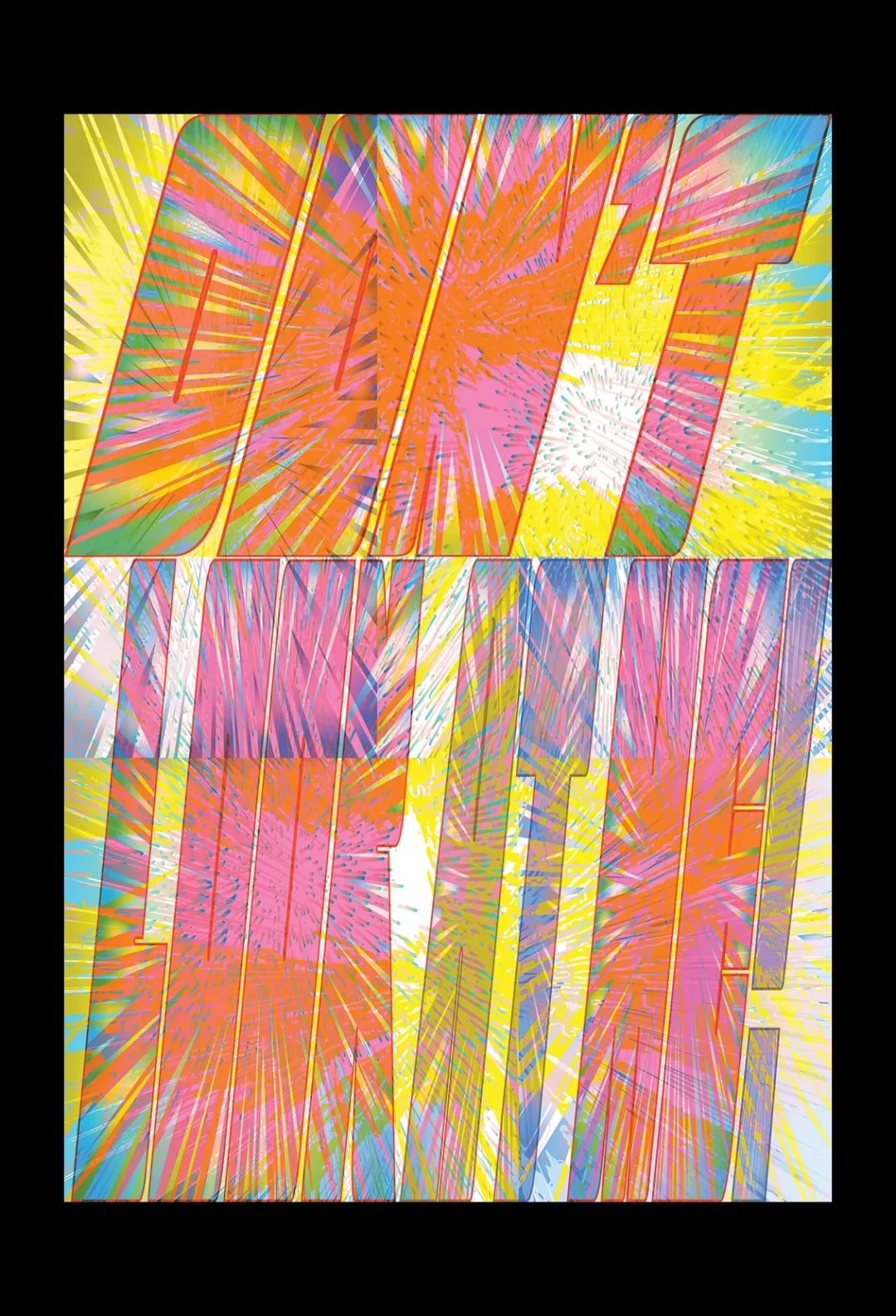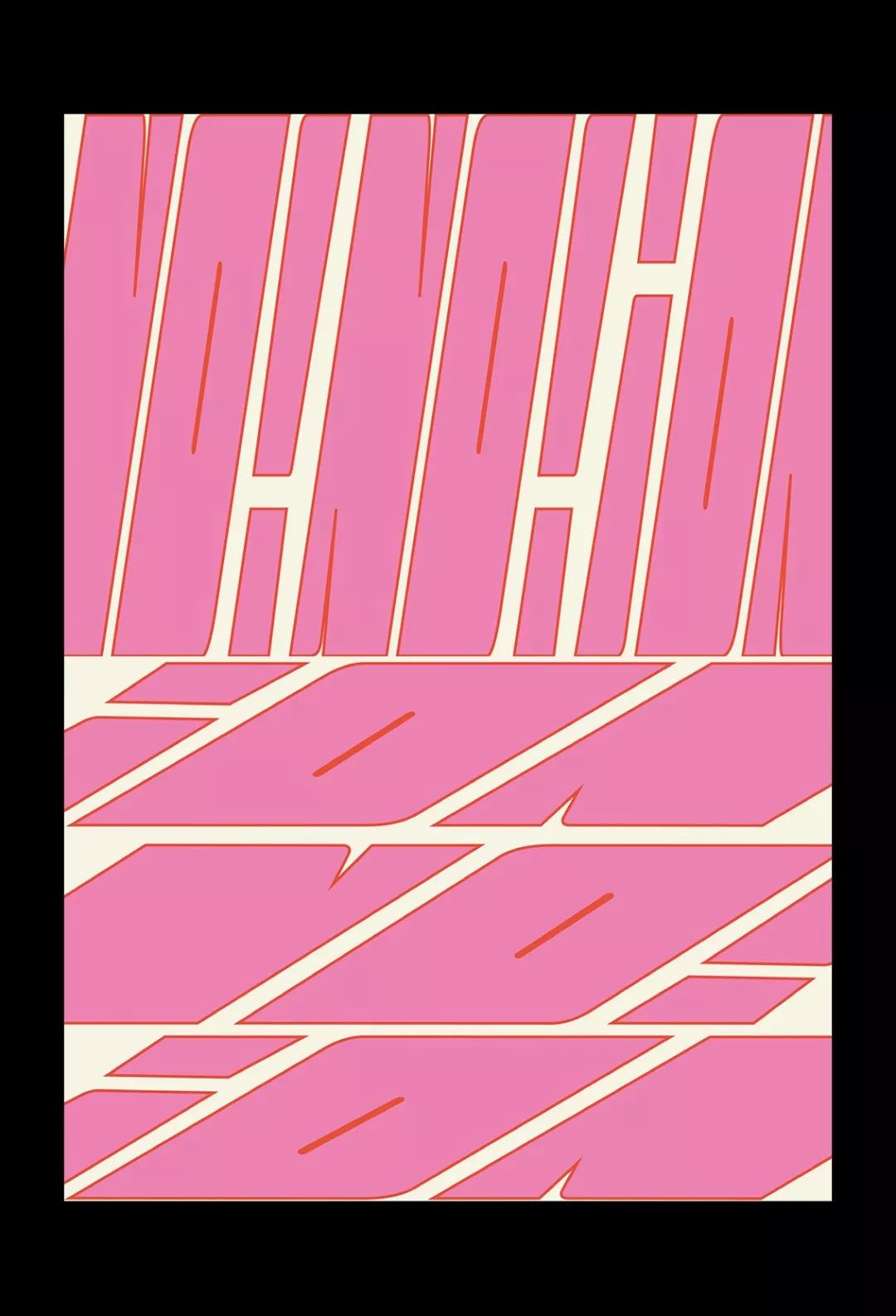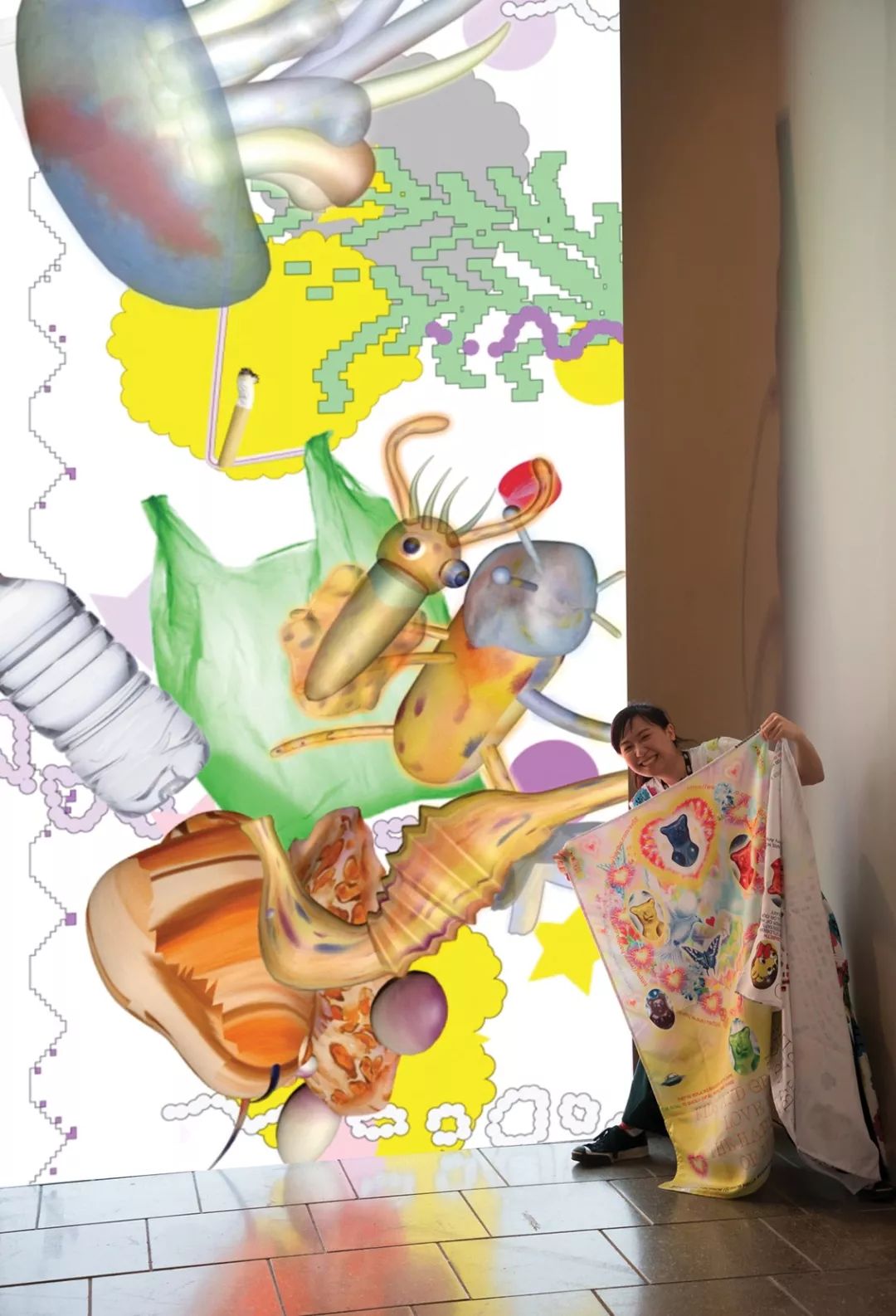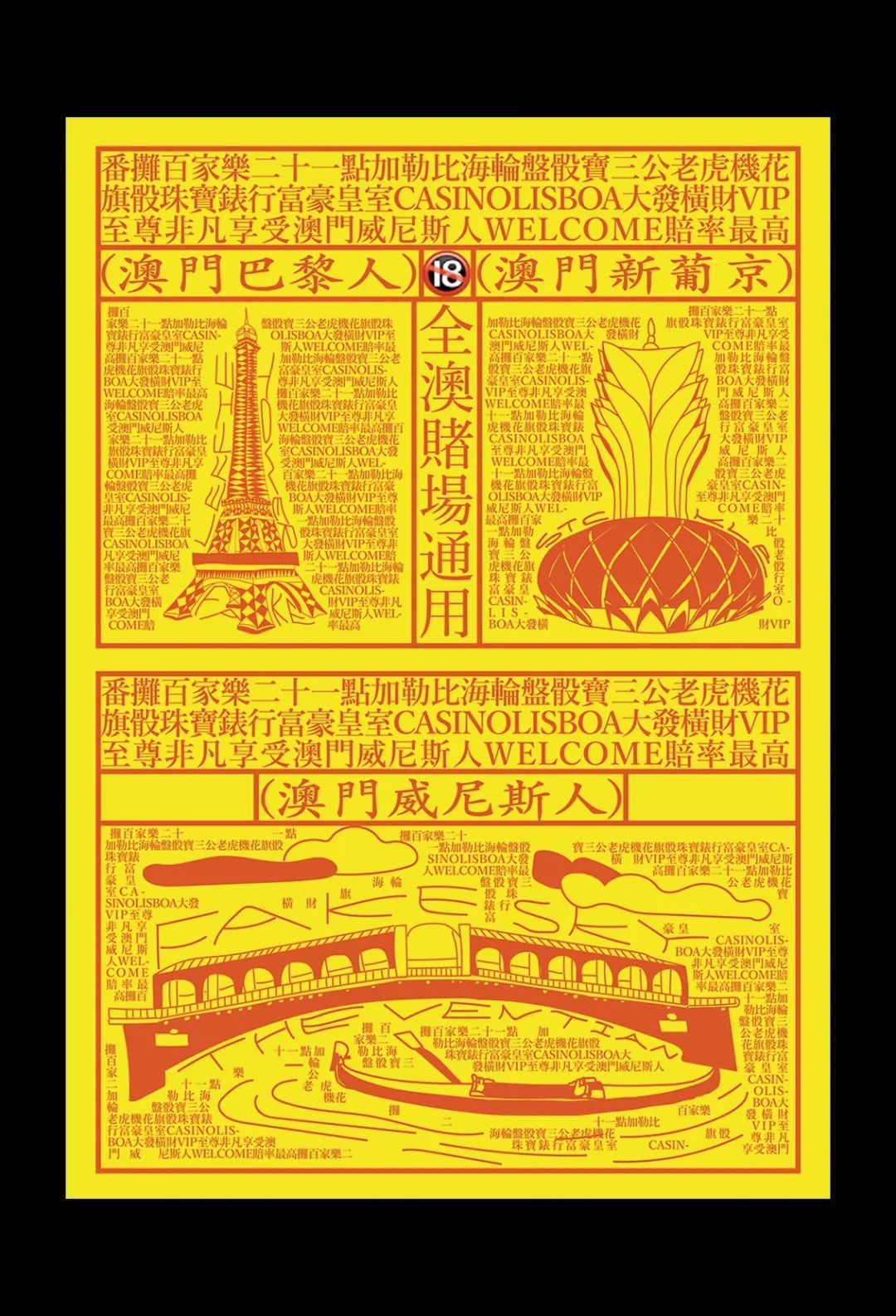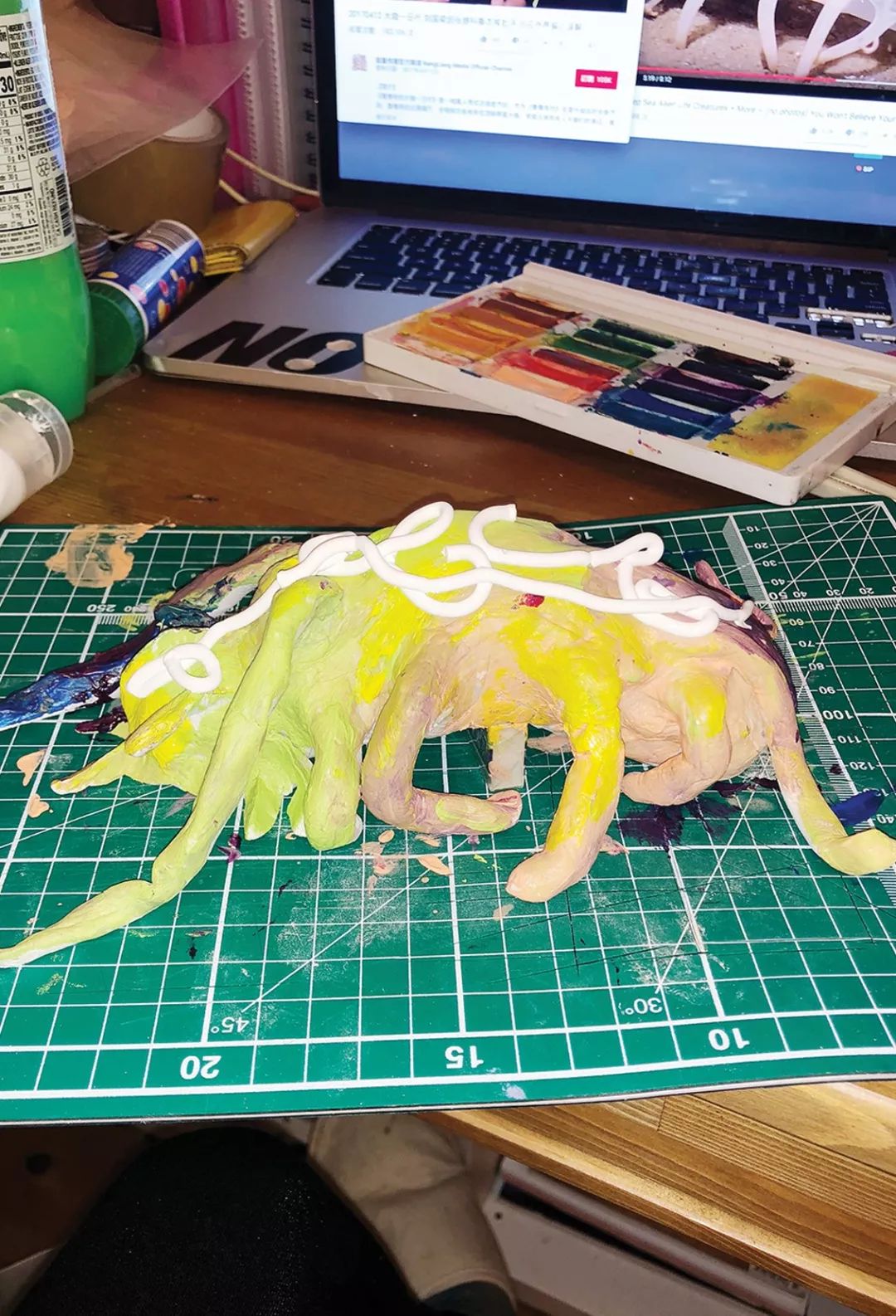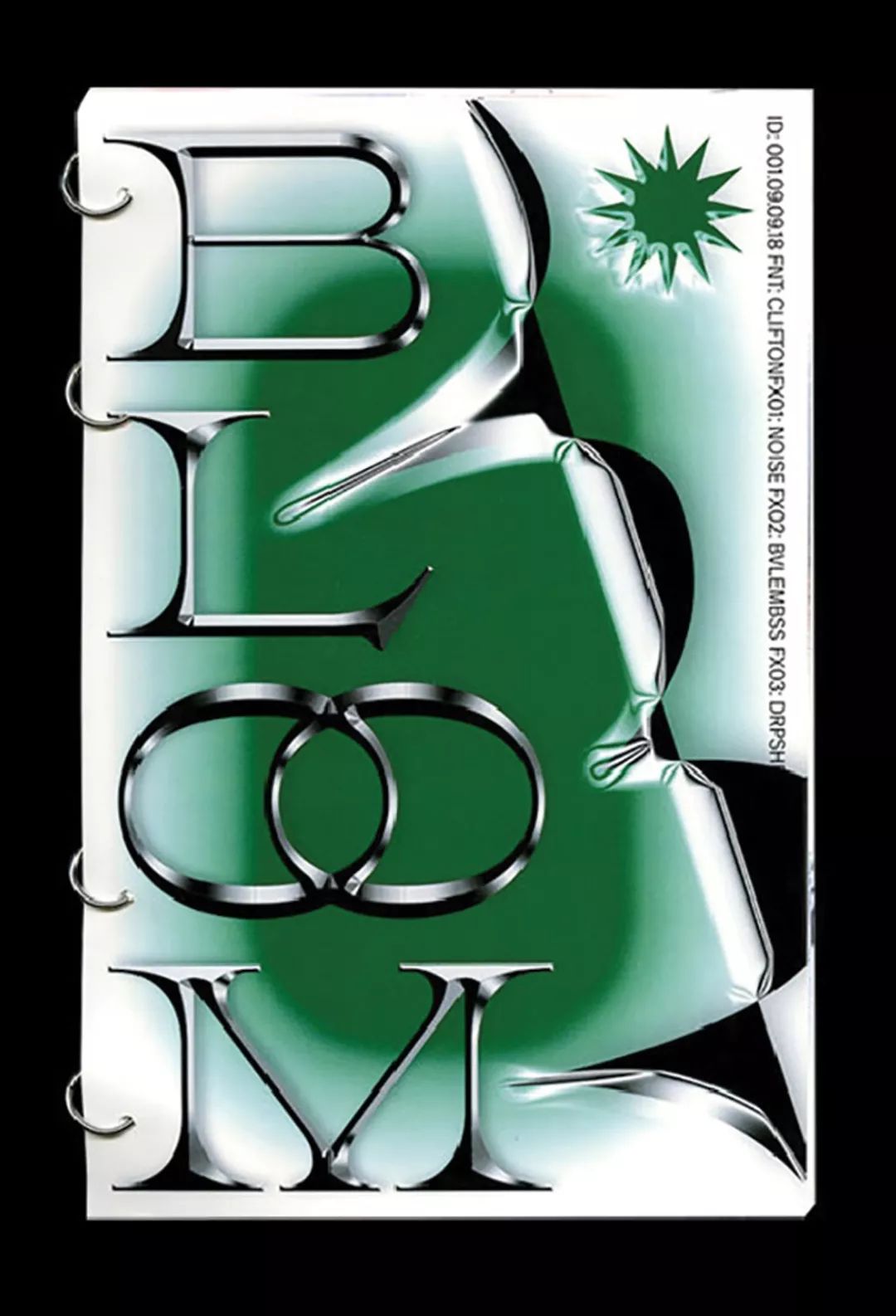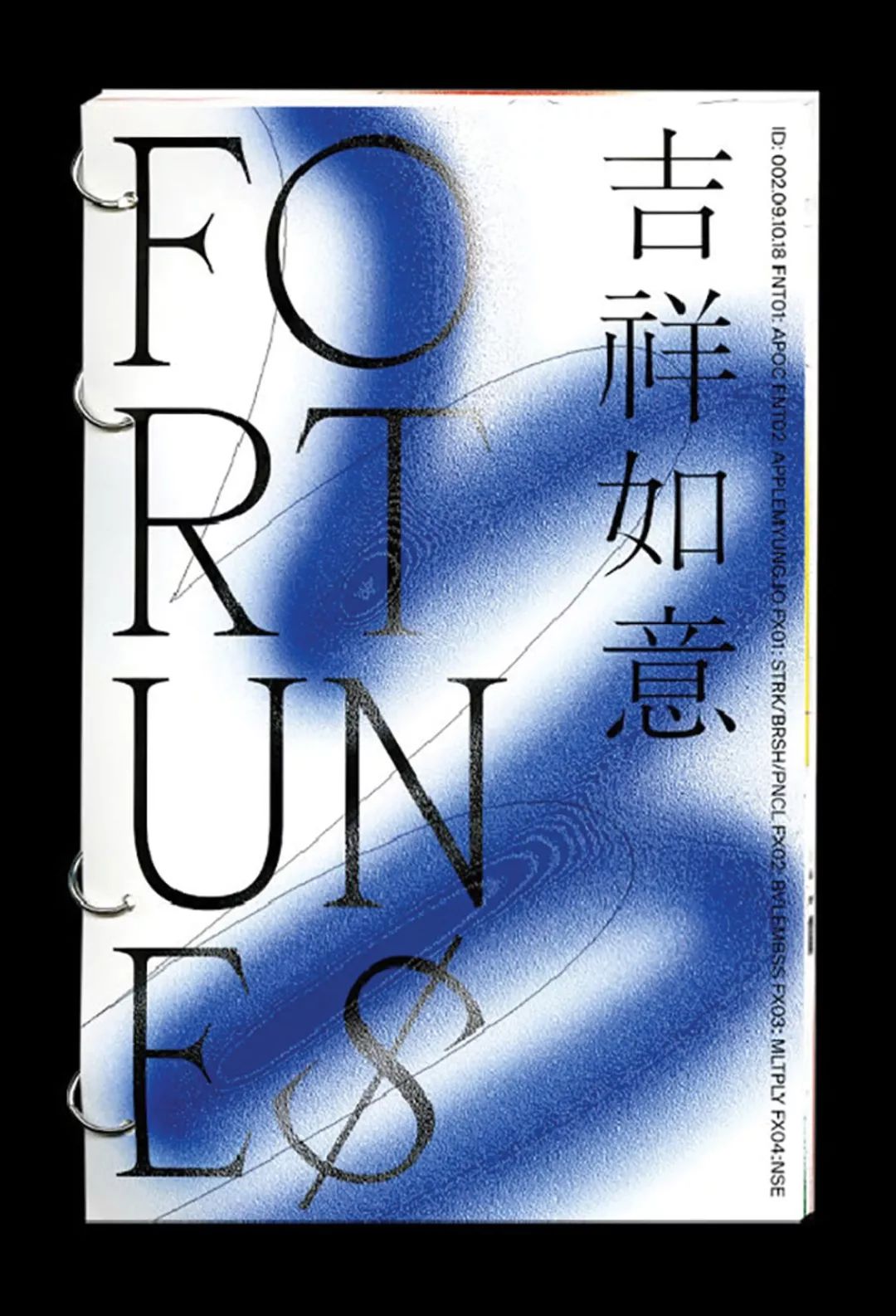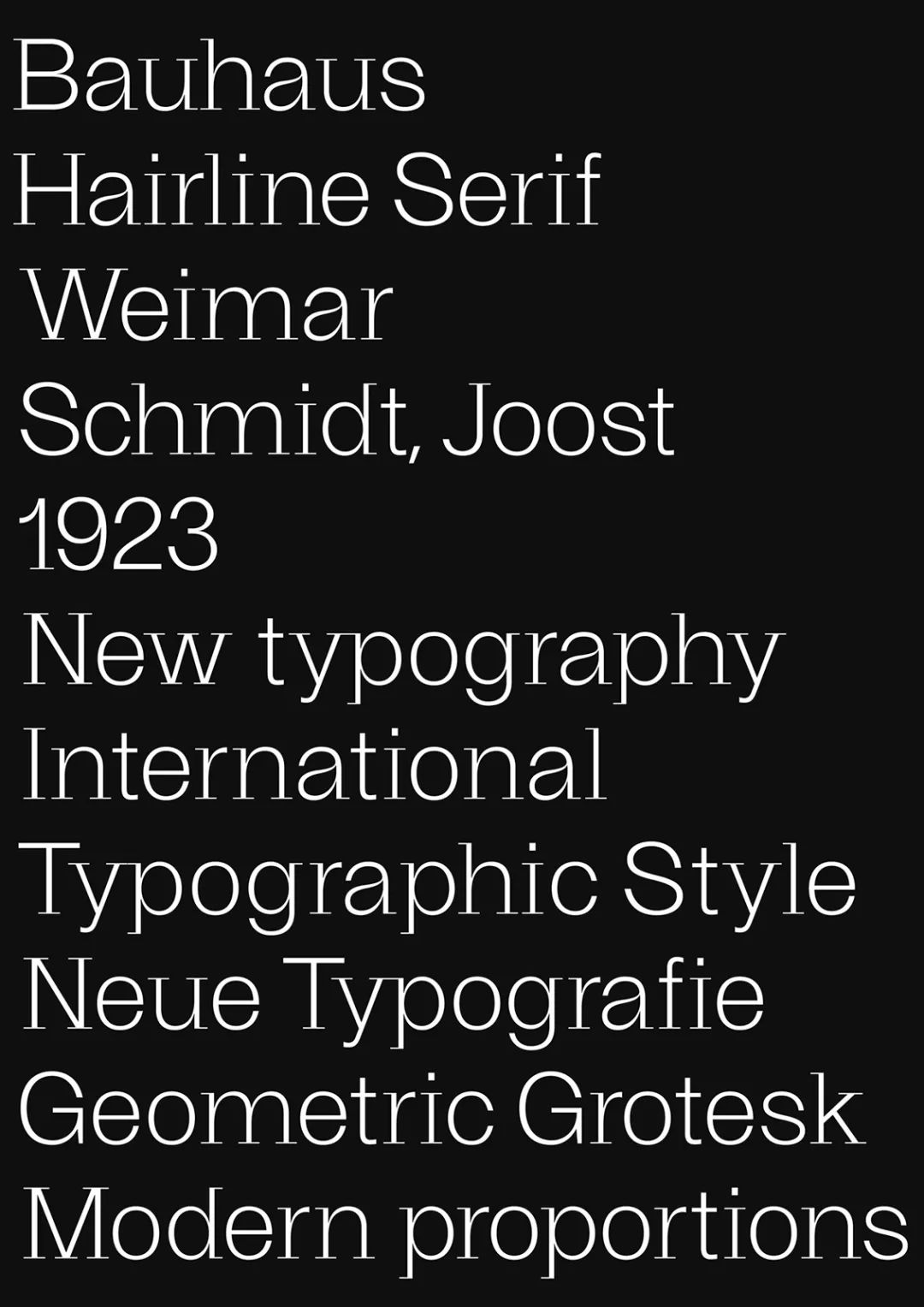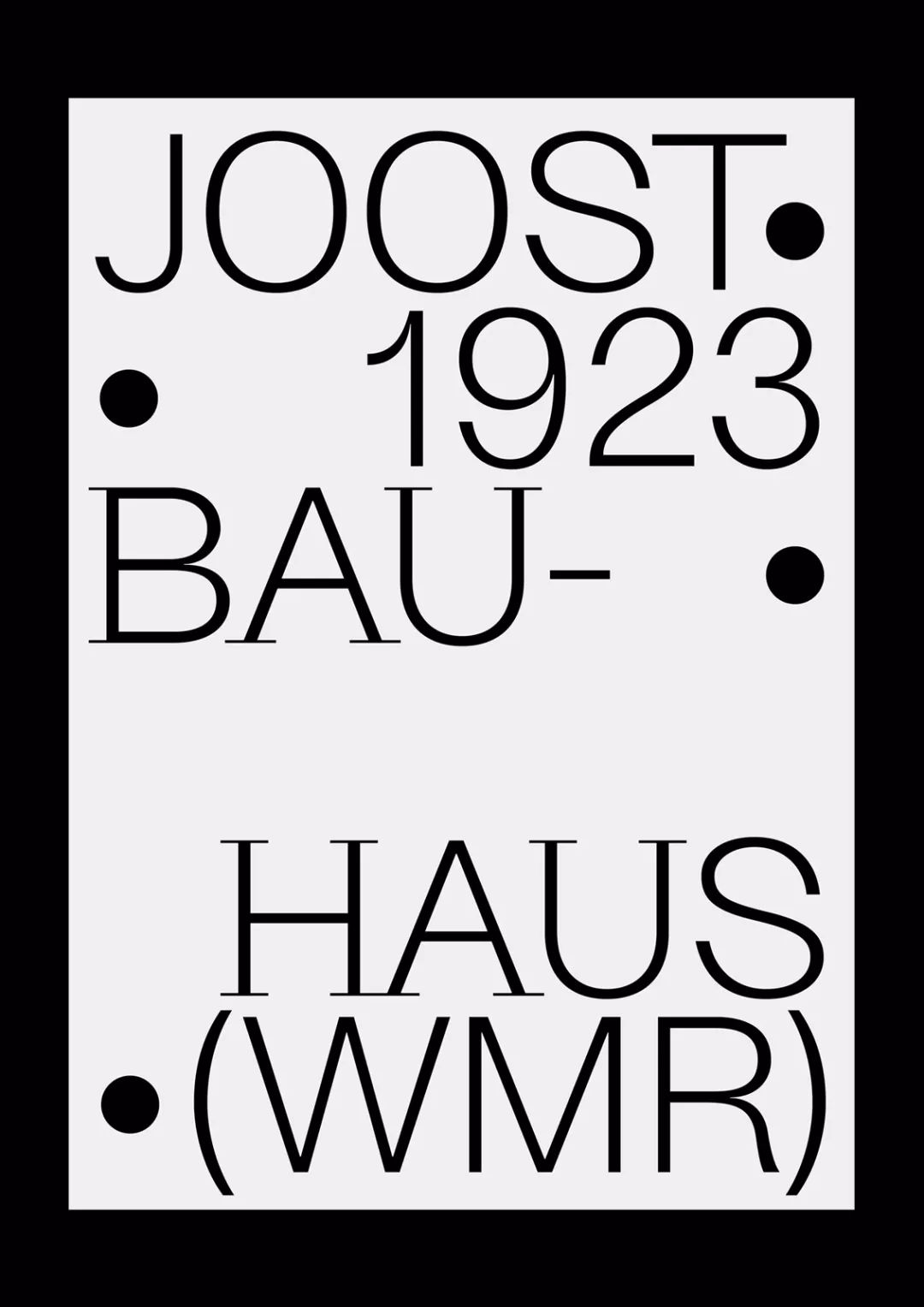
看看这18位2019年最具潜力的毕业生作品
It's Nice That 是一个艺术创意网站,为了发掘和支持新锐的设计力量,2009年开始,它发起了 The Graduates 项目:每年选择一些刚刚毕业、但是很有发展潜力的设计师,涉及平面设计、插画、摄影、动画等领域,为他们的设计实践提供支持。昨日,It's Nice That 公布了 2019入选名单:总共有 18个人脱颖而出。
The Graduates 项目没有限制自己的课程规模,将去年的15名扩展到现在的18名非常有才华的毕业生 - 这是迄今为止最多的。创造性工作,就其本质而言,是广泛的,今年的阵容是对事实的证明。2019届毕业生的特色包括平面设计师、插画家,数字艺术家,陶艺家,摄影师和动画师,以及瑞士,德国和匈牙利等地学生。
因此,需要花一些时间来了解这群优秀的应届毕业生。今日我们先从官方内容中摘取4位平面设计专业学生做相关介绍。
Suzy Chan(陈绮雯)是一位平面设计师,来自中国澳门/广东。2019年毕业于伦敦艺术大学伦敦传媒学院的一等荣誉学位。她将平面设计看作一个公共平台,而不仅用于商业交流,还用于(社会性的)自我表达。对于媒介,她之前专注于基于印刷的设计,她目前正在扩展她的数字化学习。此外,生活的背景使她对许多社会现象和问题有不同的见解。
Casino City
Adjustable Typeface
Casino City
Plastic Planet
The Haribo Cult
谭燕玉(Stefanie Tam)开发了自己独特的风格,用简洁的视觉语言融合了对文化和社会政治体系的批判性审视。
这位洛杉矶的平面设计师曾在 Wax Studios,Stink Studios,TPM Magazine 和 The Underground Museum 工作过。她毕业于加州大学洛杉矶分校的设计媒体艺术学士学位课程,很快将在耶鲁大学艺术学院攻读平面设计硕士学位。Stefanie 项目的关键,特别是她广泛的自发项目,是她对多模态的重视。她的项目采取研究,档案,书籍,网站,照片和装置的形式,所有这些都在她探索一个中心概念的过程中占有同等的分量,它们交织在一个交叉参照的系统中,每一种媒介都增加了意义层。
A Love Letter to LA
她说,在攻读学位期间,Stefanie对“信息结构如何影响解读”变得“越来越感兴趣”。她作为一名设计师的优势在于她能够在视觉系统中进行高度概念化的思考,这种视觉系统具有吸引力,紧凑和清晰 - 充满意义,密集的信息和外部参考,但没有炫耀。这些系统虽然视觉上简洁,但在结构和概念上都很复杂,每个元素都与另一个元素通信(或相互作用),并努力塑造读者、观众或用户体验。
例如,她的多方面个人项目--i.do/not_think?I=know_what&I_do_not=know,是对数据信息存档的扩展练习,同时询问信息的生成,消费和消化方式。很少有设计师有能力以这样一种高度概念性的方式思考,也很少有设计师有能力构建与之匹配的设计系统。显然,斯蒂芬妮拥有这两种能力。
Poster Designs
//OFPLACE
FROM WASTE TO CHANGE
Laura Csocsán 的作品,因为它缺乏色彩,充满了流畅,精心研究的图形设计和印刷作品。她是一个完全坚持形式而不是功能的设计师(坚持形式高于功能),允许概念指导她的实践——在她的项目中,没有一个决定是无法解释的。
Laura 在匈牙利长大,现居住在布达佩斯的首都,她毕业于莫霍里纳吉艺术与设计大学,与朋友和以前的同学共用一个工作室。通常,她的项目从排版开始,然后有条不紊地展开,从一点信息或灵感到另一点,进行有条不紊的扩展。事实上,正是平面设计的逻辑在她十几岁的时候就吸引了她进入媒体行业,如今,她把同样的逻辑应用到她作为平面设计师和印刷师的自由职业生涯中。
Laura 的作品集虽然保持了单调,但绝不缺少变化。年轻设计师承担的每个项目都有定制字体和完全开发的字体,这些字体源于理性思考,但执行与才华和个性。Laura 现在计划继续攻字体设计硕士学位。
ECAL 的毕业生 David Massara 并不满足于仅仅创造出令人印象深刻的精美设计作品,他开始着手的每一个项目都像是一个拼图,他需要把它们拼在一起。作为一个完全遵循平面设计的创意学科强加给从业者的结构的设计师,David 在每一个项目的开始都有一个漫长的研究过程。
其结果是项目与背景分层,不管他是在建立一个网站,还是为一本关于他对爵士音乐热爱的书制作一个门框。这个早期的研究也告诉了他令人印象深刻的设计选择和属性,这个早期的研究也告诉他令人印象深刻的设计选择和属性,每个项目都仔细选择正确的字体,正确的色调,以及完美的布局。
David 是一位注定要在未来的岁月里塑造我们周围图形世界的设计师,他的激情 - 尽管受到限制 - 尽管有所克制——展示了一名毕业生对媒体丰富历史的敬意,以此来告知他的未来。